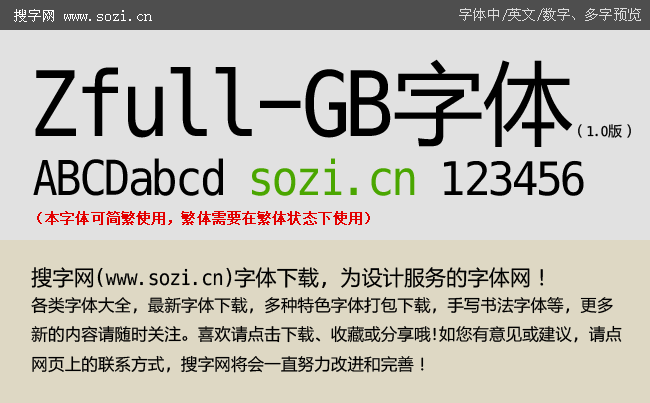
正體(簡(jiǎn))中文點(diǎn)陣字Zfull-GB
搜字網(wǎng)提供一款正體(簡(jiǎn))中文點(diǎn)陣字Zfull-GB中文字體下載,正體(簡(jiǎn))中文點(diǎn)陣字是一款字形端莊的中文藝術(shù)字體,字體簡(jiǎn)潔端正,莊重大方。GBK碼收錄字體更全,適合應(yīng)用于廣告設(shè)計(jì)、名片設(shè)計(jì)、包裝印刷、產(chǎn)品設(shè)計(jì)等應(yīng)用。